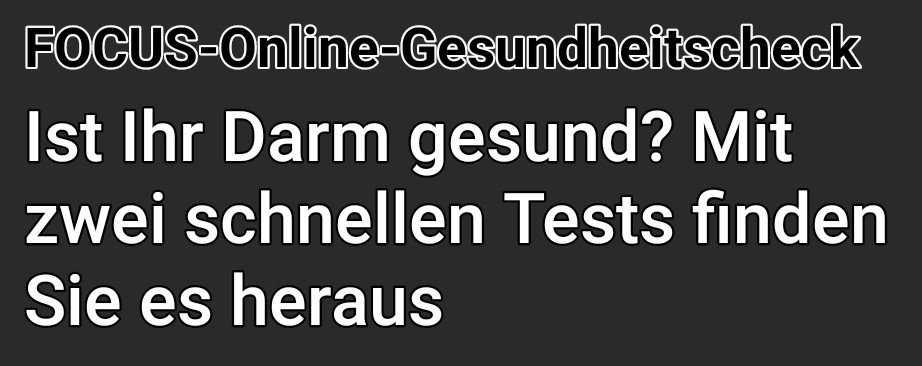
Zweite Schriftart beim Galaxy Tab S8 Ultra ändern
da ich eine Augenerkrankung habe, die einige Sehprobleme verursacht, habe ich beim Tab S8 Ultra den Dark-Mode gewählt und die Schriftgröße und den Bildschirmzoom auf ziemlich groß gestellt. Bei der Schriftart habe ich Gothic Bold gewählt. Nun scheint Android aber zwei Schriftarten zu verwenden, denn z.B. bei What's app oder auch im Playstore und in Nachrichten-Apps und anderen Apps werden einige "Untertexte" in einer bestimmten Konturschrift dargestellt, die ich sehr unleserlich finde. Icjh habe die vorhandenen Schriftarten durchprobiert, aber immer wird als zweite Schriftart eine Konturschrift verwendet, wo mit ich absolut nicht klarkomme, weil ich die kaum lesen kann.
Weiß jemand, ob die fest eingestellt ist, oder ob man die ändern kann. (im Hell-Mode ist das glaube ich nicht so)
Meinst du ev kontrastreiche Schriftart?
Eingabehilfen/Kontrastreiche Schriftarten
Vlt ein Screenshot mal einstellen
Dies ist ein Screenshot vom Tablet aus einer Nachrichten App. Der Text "FOCUS-Online-Gesundheitscheck" ist in Konturschrift. Diese Konturschrift taucht in ganz vielen Apps auf. Der dünne weiße Strich ist schwer lesbar. Ich möchte die Buchstaben ganz in weiß. Auf meinem alten Tablet Tab S8 ist in genau den gleichen APPs beim gleichen Text keine Konturschrift. Die Schrift muss also von Android kommen. Wenn ich unter Einstellungen die Schriftart ändere, ändert sich die Schriftart bei "Ist ihr Darm gesund?..." Der Text oben aber bleibt in Konturschrift.
Vielen Dank. Das war tatsächlich die Lösung. Ich hatte kontratreiche Schriftarten eingestellt, weil ich dachte, dass das die Lesbarkeit verbessert. Das hatte ich dann aber ganz verbessert. Und dadurch kam das. Ich muss deutlich sagen, dass kontrastreiche Schriftarten die Lesbarkeit im Dark Mode verschlechtern. Vielen Dank
du mußt 'Kontrastreiche Schriftarten' ausschalten.
Zu finden unter 'Eingabehilfen'
Das ist was ich schrieb unter # 2